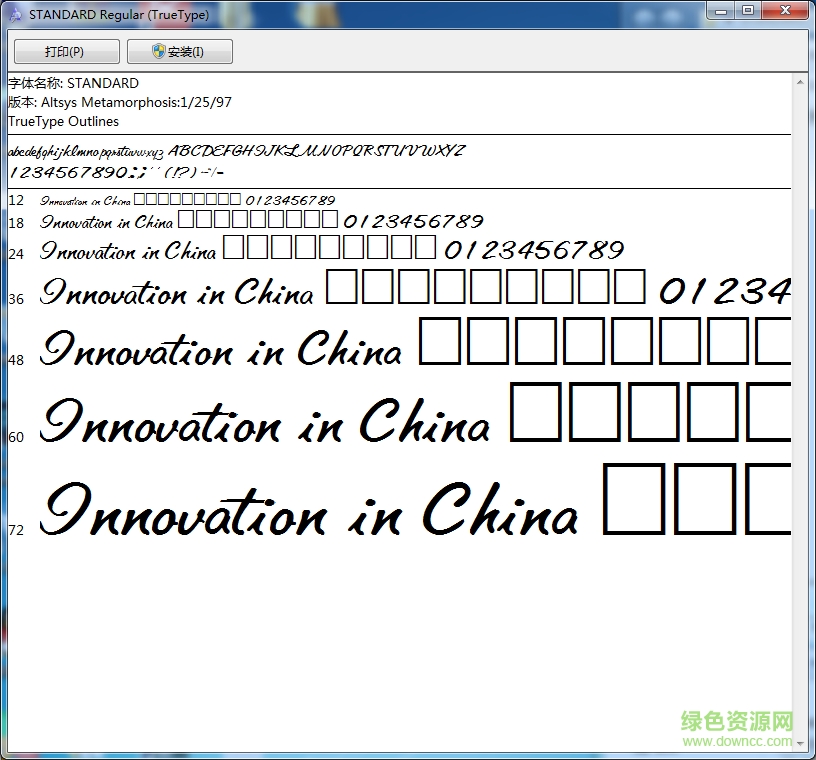
standard字體是一款常用于cad制圖軟件中非常有個性的字體軟件,字體大方飄逸極具個性,支持英文漢子數(shù)字等多種方式輸入顯示,可直接導(dǎo)入CAD軟件中使用??靵砭G色資源網(wǎng)下載體驗吧!
standard字體這款字體是真的很不錯,不僅字形特別美,還特別實(shí)用,可以用在很多方面。